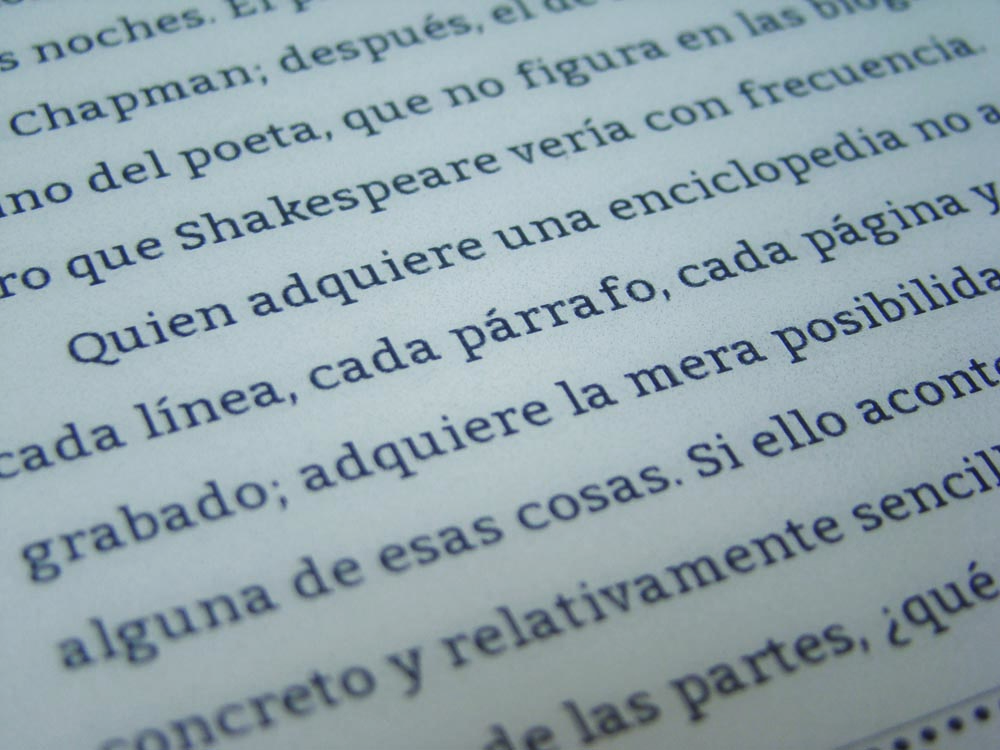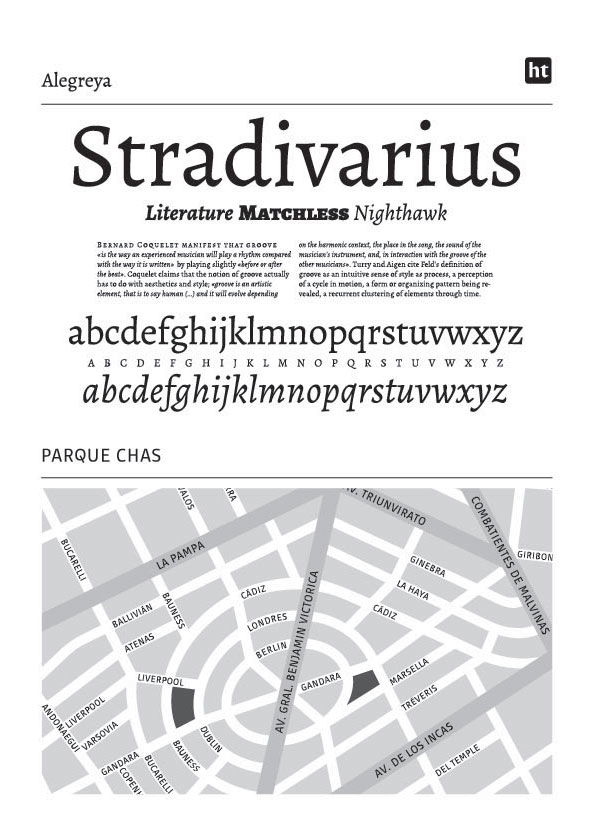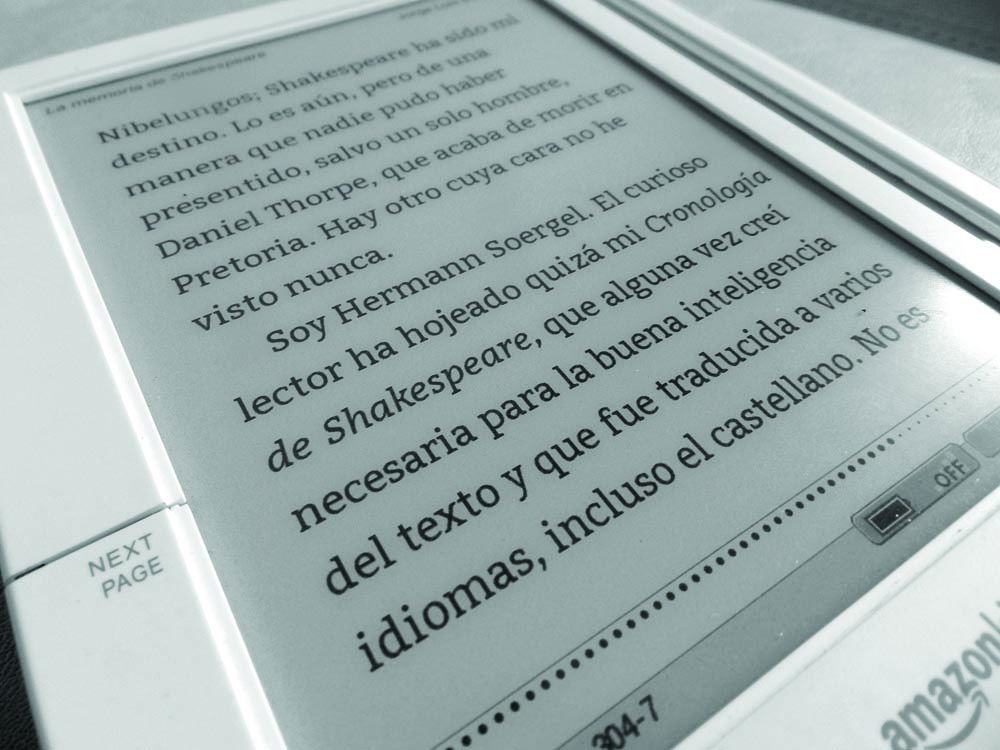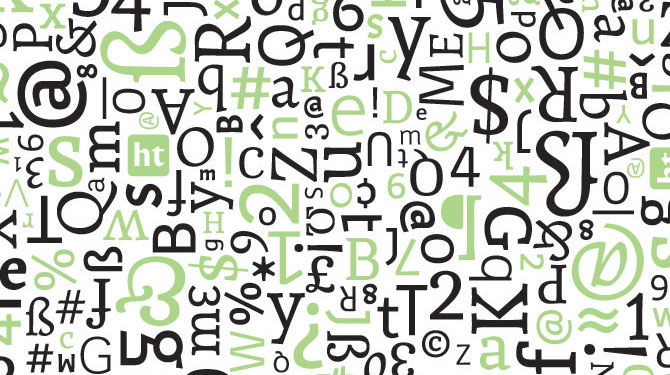
Las tipografías que se cultivan en Argentina
Venían de Mendoza, Rosario o Buenos Aires pero, finalmente, coincidieron en la universidad de la capital argentina. En un país en el que, a la vuelta de clase, lo normal es hablar del descenso de River o de lo último que dijo Cristina Fernández de Kirchner, ellos mataban el tiempo hablando de anatomía de letras, trackings o cajas. Todos se estaban especializando en diseño tipográfico y aquello fue el inicio de Huerta Tipográfica, un proyecto que unió sus carreras.
La Facultad de Arquitectura, Diseño y Urbanismo de Buenos Aires quedaba un poco retirada del centro de la ciudad. Pablo del Peral, Carolina Giovagnoli, Sol Matas y Andrés Torresi comenzaron a compartir colectivo de regreso a casa y formaron piña. “Nos reuníamos después de ir a clase para comer y dibujar tipografías. Así empezamos a cooperar presentando nuestros trabajos y pensando nuevos proyectos”, cuenta Sol Matas.
En 2009, fundaron Huerta Tipográfica “de manera tímida, bautizando el proyecto, creando unas tarjetas y una web”. El grupo, que se generó como un espacio de reunión y colaboración, se convirtió rápidamente en el medio con el que los cuatro diseñadores expresan su veneración hacia la tipografía. Ven a este campo del diseño como un producto cultural y están muy motivados por participar en el auge que está experimentando la disciplina en el país americano.
“En la actualidad se está promoviendo el barrio de Barracas como distrito centrado en el diseño, principalmente para promover su incorporación como herramienta de competitividad. Se están gestando muchas actividades en torno al diseño gráfico, al diseño industrial, a la moda y a los medios audiovisuales”, explica Matas. La creadora cree que internet y la tecnología están democratizando la producción y distribución de tipografías aunque “el cambio en los modelos de creación, producción y distribución no siempre significa una mejora de calidad en el campo tipográfico”.
Para Huerta Tipográfica, el proceso de gestación de un trabajo suele comenzar con una investigación que dote de un sentido a la idea que quieren desarrollar. Les gusta mirar a los referentes históricos y tomar buena nota de lo que ya se ha hecho, pero insisten en reinterpretar todo lo que ven para convertirlo en algo nuevo.
Posteriormente, pasan a la etapa de dibujo, en la que moldean el primer vistazo que ofrece la fuente al usuario. “Puede comenzarse en el papel o directamente en el ordenador. Aquí se definen las pautas estructurales y las rasgos estéticos del proyecto”, detalla la diseñadora argentina.
A partir de ahí, y con la definición de unos cuantos signos, los diseñadores comienzan a ver el comportamiento de las palabras y los párrafos. Es entonces cuando comienza la etapa de producción de la tipografía. Las letras no hablan únicamente según se combinen. Sus líneas determinan un carácter, otro mensaje implícito, que puede enriquecer el significado de lo que se escribe. “Aquí es donde se terminan de poner a prueba las tipografías y se realizan todos los ajustes necesarios para que todo funcione correctamente en las distintas plataformas”, remarca Sol Matas.
Explican estos hortelanos del carácter que “los nuevos formatos como las webfonts —en particular, el catálogo de Google— han sido piezas importantes en la producción de fuentes en Argentina este último año”. La difusión que tiene la plataforma de Google ha hecho que muchos amantes del diseño tipográfico dieran el salto del amateurismo a un enfoque más profesional de esta labor. “Es muy difícil dedicarse a la profesión si se focaliza en el mercado local porque es casi inexistente”, lamenta Matas. Por fortuna, el aperturismo tipográfico que están proporcionado las nuevas posibilidades que ofrece el diseño web está otorgando oportunidades a los creadores de letras.